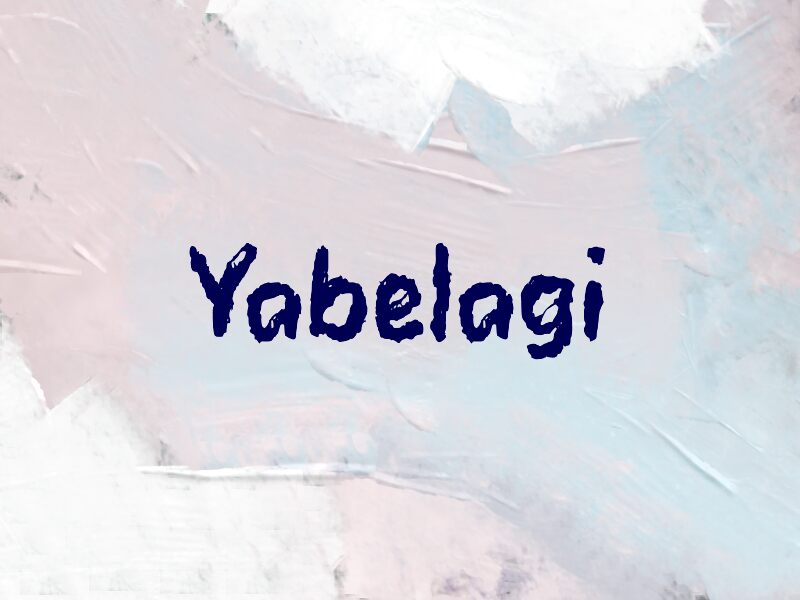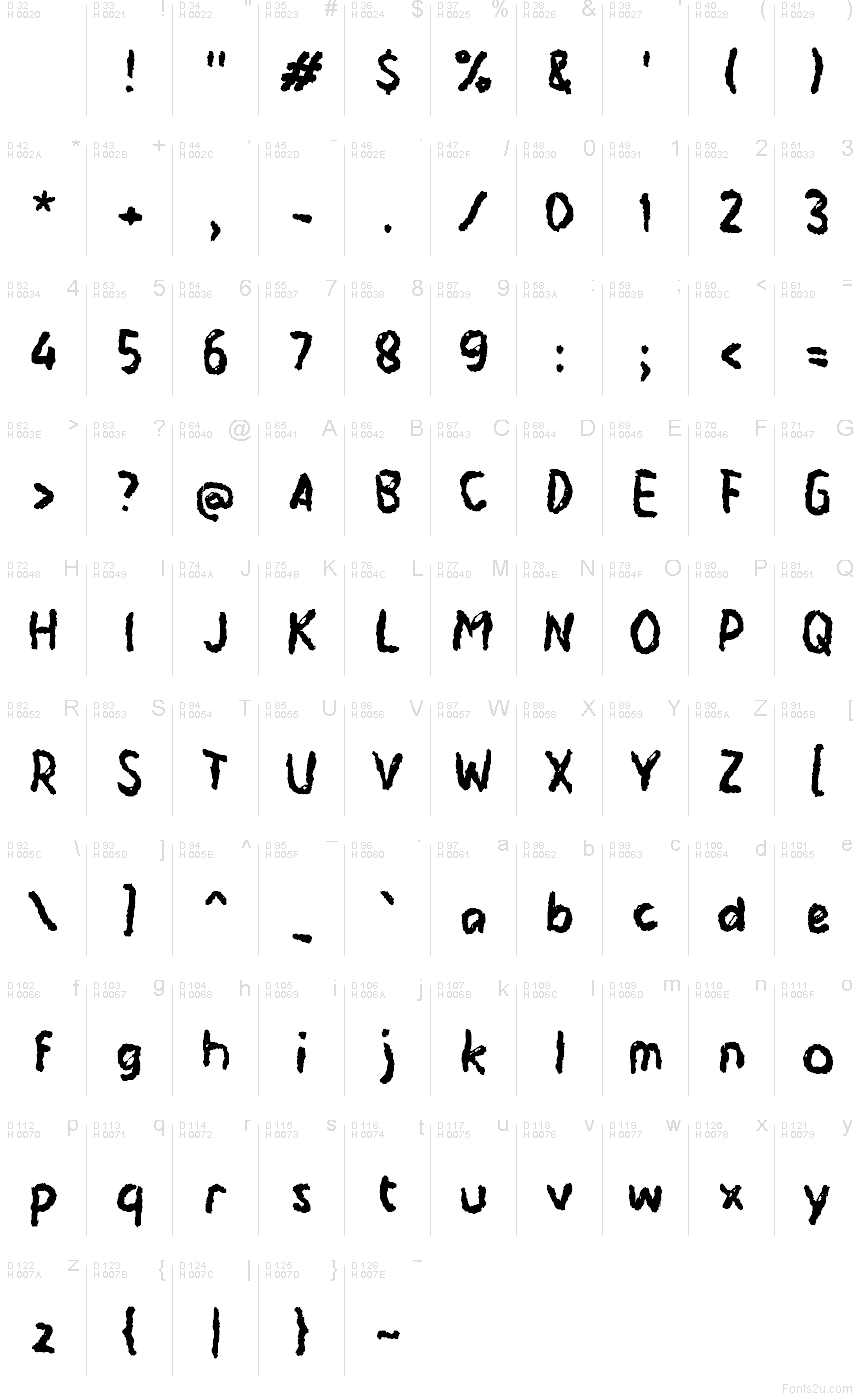
Yabelagi
Yabelagi da Wep é uma fonte display gratuita no estilo trash, definida por uma textura áspera e esgarçada que faz com que cada letra pareça ter sido raspada em tinta molhada. Essa superfície quebrada permeia todo o design, dando às letras uma presença suja e artesanal, em vez de um efeito de desgaste artificial aplicado por cima.
Flyers de música, fanzines underground, títulos de terror, gráficos de skate e cabeçalhos de pôsteres fazem todo o sentido com esta fonte, especialmente quando o layout exige algo cru em vez de ordenado. As bordas irregulares e o ritmo errático conferem aos textos curtos de embalagens ou promoções de eventos um impacto direto e autêntico que fontes mais polidas acabariam por suavizar.